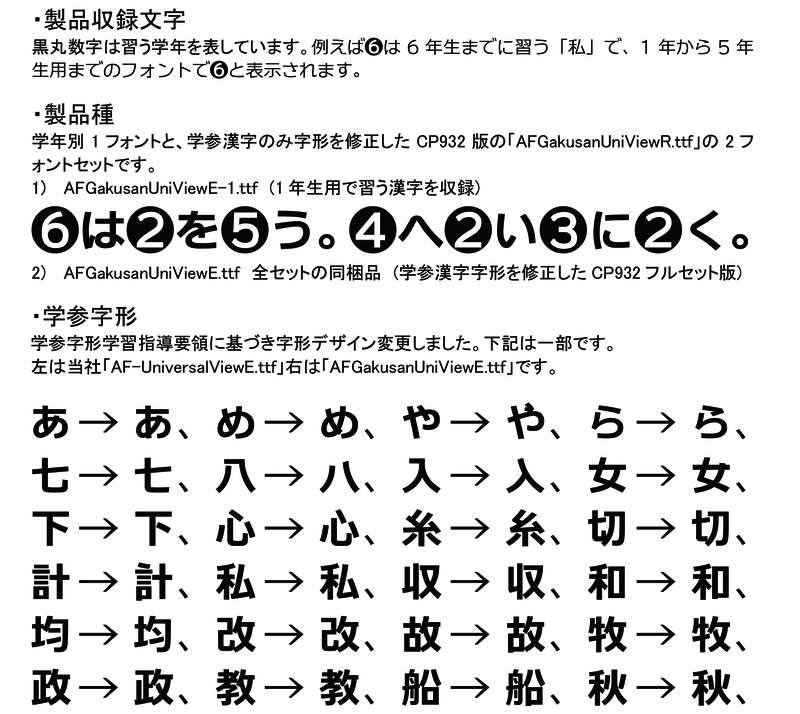
可読性を重視したユニバーサルビューのレギュラーをベースに文部科学省学習指導要領の字形を再現、他に類を見ない学年別学参フォントをご案内します。ドリル等教材用はもちろん児童を対象とした配布資料作成に最適です。その対象学年までに習う文字を収録したフォントと学参漢字のみ字形を修正したCP932フルセット版の2書体セットです。